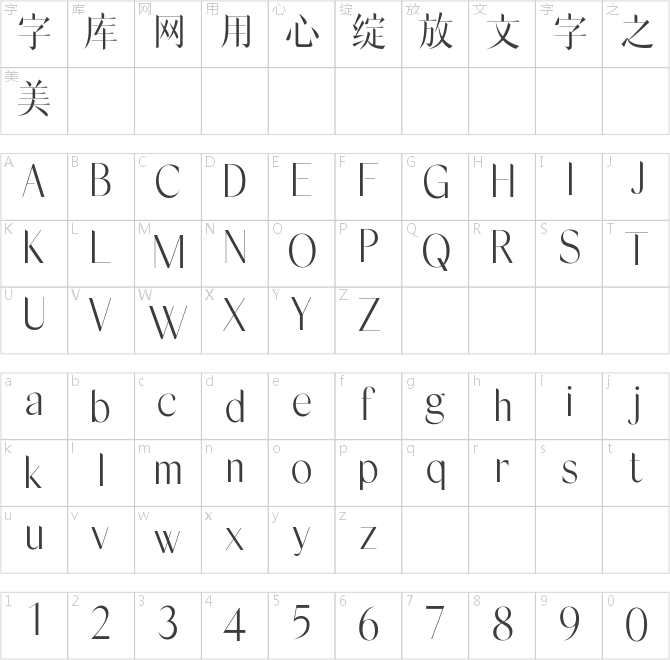
火山字型 眉月 S01 詳情頁
火山字型
火山字型 眉月 S01字體下載眉月字體
定位于當(dāng)下視覺審美趨勢,可在標(biāo)題展示類應(yīng)用場景中廣泛使用。時尚、美妝、文化、娛樂等行業(yè)推薦使用。
眉月,采用傳統(tǒng)宋體的小中宮處理,借鑒了港臺版的舊字形風(fēng)格,在體飾上盡量簡化,僅保留宋體字的基本風(fēng)格。外形上縮減了字面的寬度,使其呈現(xiàn)出修長秀麗、優(yōu)雅清新之勢。封口橫畫收筆留白,增加設(shè)計感與靈動性。各筆畫的處理犀利、清勁、峻朗、風(fēng)骨兼?zhèn)洌w結(jié)構(gòu)清晰、脫俗、內(nèi)斂,有著強烈的人文氣息。